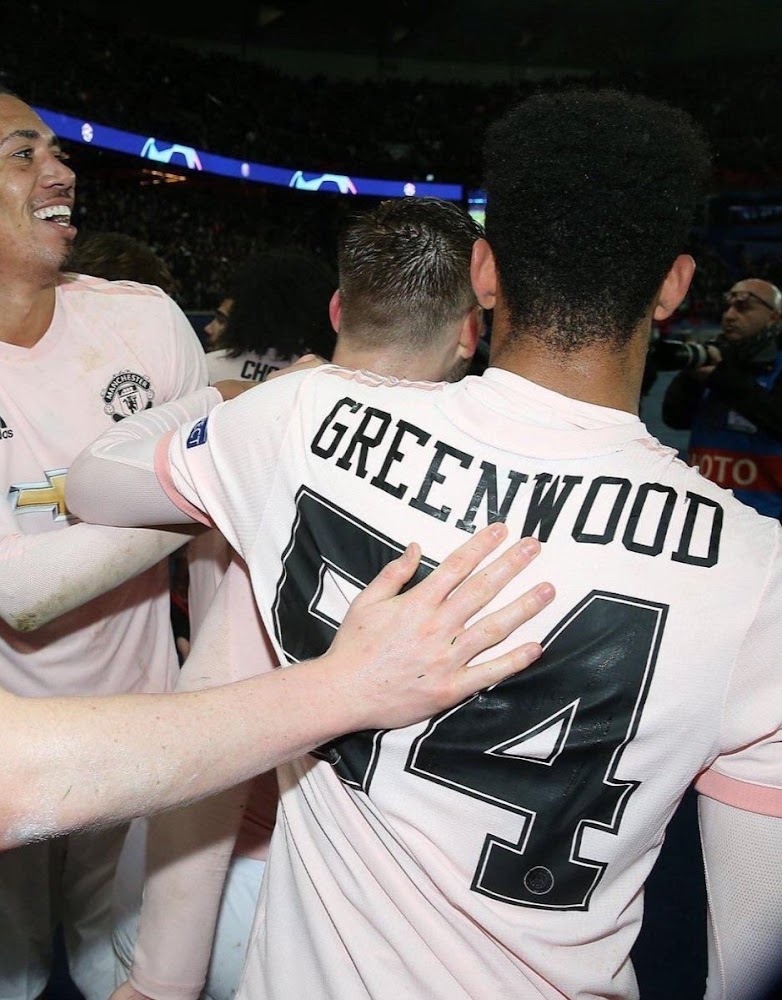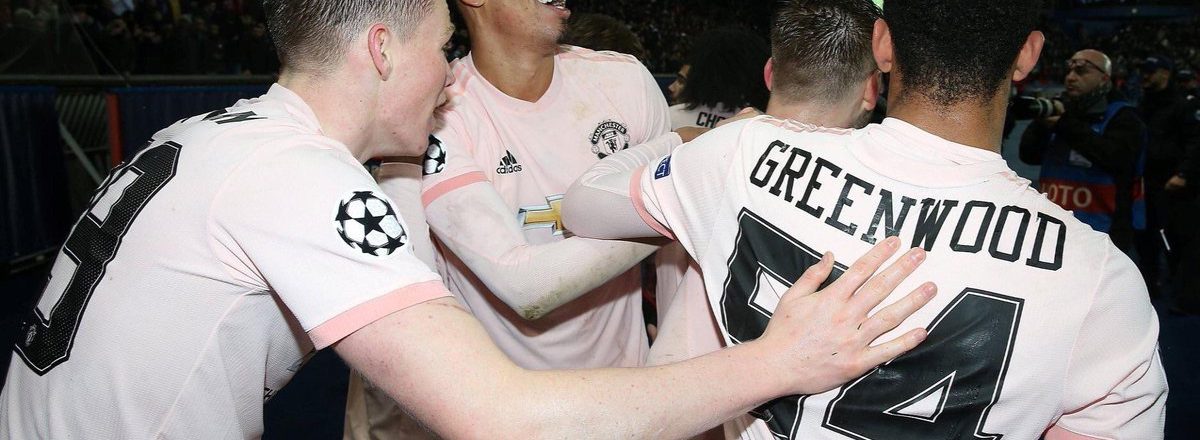
VERRÜCKT: ManU verwendet PSG-Schriftart für Youngster gegen PSG
Manchester United feierte in der letzten Woche ein unglaubliches Comeback in der UEFA Champions League gegen PSG. Am Donnerstag hat sich herausgestellt, dass der junge Manchester-United-Spieler Mason Greenwood PSGs Nummernstil gegen PSG verwendet hat. Vielen Dank an @Kurillos.
ManU beflockt Greenwoods Trikot im PSG-Store erst 2 Stunden vor Spiel
In den letzten Minuten des Spiels rief ManU-Trainer Ole Gunnar Solskjær den 17-jährigen Mason Greenwood zur Einwechslung. Es war Greenwoods A-Debüt für Manchester United (er spielte bisher nur in den Jugendteams von ManU). ManU bereitete jedoch in Manchester kein Trikot für ihn vor und so spielte er das Match mit der gleichen Schriftart wie Paris Saint-Germains Spieler.
Die Beflockung hätte erst 2 Stunden vor Spielbeginn stattgefunden (wiederum laut @Kurillos).
Von Michael Jordan & Chicago Bulls inspiriert - Jordan Paris Saint-Germain 18-19 Champions League Trikot-Schriftart veröffentlicht
Die Greenwood-Schriftart ist als PSG-Schriftart leicht zu erkennen - sie trägt das PSG-Logo am unteren Ende. Die PSG 19-20 Jordan Champions League Schriftart wurde von den 1998 Chicago Bulls Trikots inspiriert.